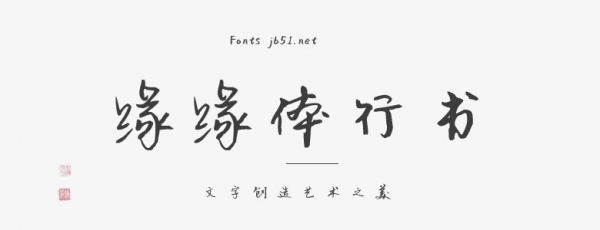
緣緣體行書(緣緣體行書GB2312、YUANYUANXSGB2312)作者是中國大陸的張緣緣。作者不僅人美,字也寫得很美,由廣西霽云軒字體工作室制作成字體文件分享給大家使用。這是一款適用于藝術(shù)設(shè)計方面的手寫字體,字型十分漂亮。延續(xù)了行書的行云流水,添加了自己的特色,瀟灑自如,簡單大方,看上去很整齊,無拘無束,適用于廣告設(shè)計、裝潢設(shè)計、視覺設(shè)計等。
該字體支持的6763個常用字符,簡體中文基本不缺字,繁體則相對少些。